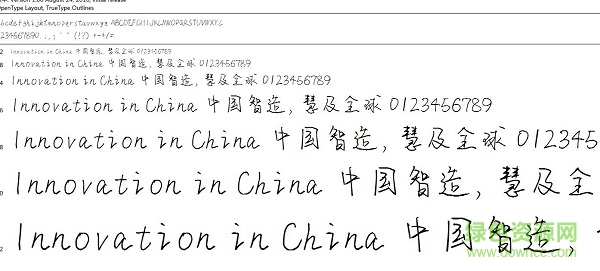
鋼筆手寫字體大全收錄了纖細手寫體、方正靜蕾簡體、郭小語鋼筆楷體、鐘齊山文豐手寫體等一系列好看的手寫鋼筆字體,美觀實用,易讀易認,可以用在平面設計方面,歡迎大家免費下載!
鋼筆字體特點
1.鋼筆書法,就是用鋼筆表現(xiàn)漢字的線條書寫和造型藝術。其“線條書寫”即用鋼筆表現(xiàn)漢字的各種筆畫的方法,其“造型”即漢字的結(jié)構和章法。
2.鋼筆字的線條表現(xiàn)形式和藝術感染力雖不及毛筆書法那樣豐富,但遠遠勝于鉛筆、圓珠筆等其他硬筆,因為鋼筆的筆尖富有彈性,寫出的筆畫同樣有粗細、輕重之分。